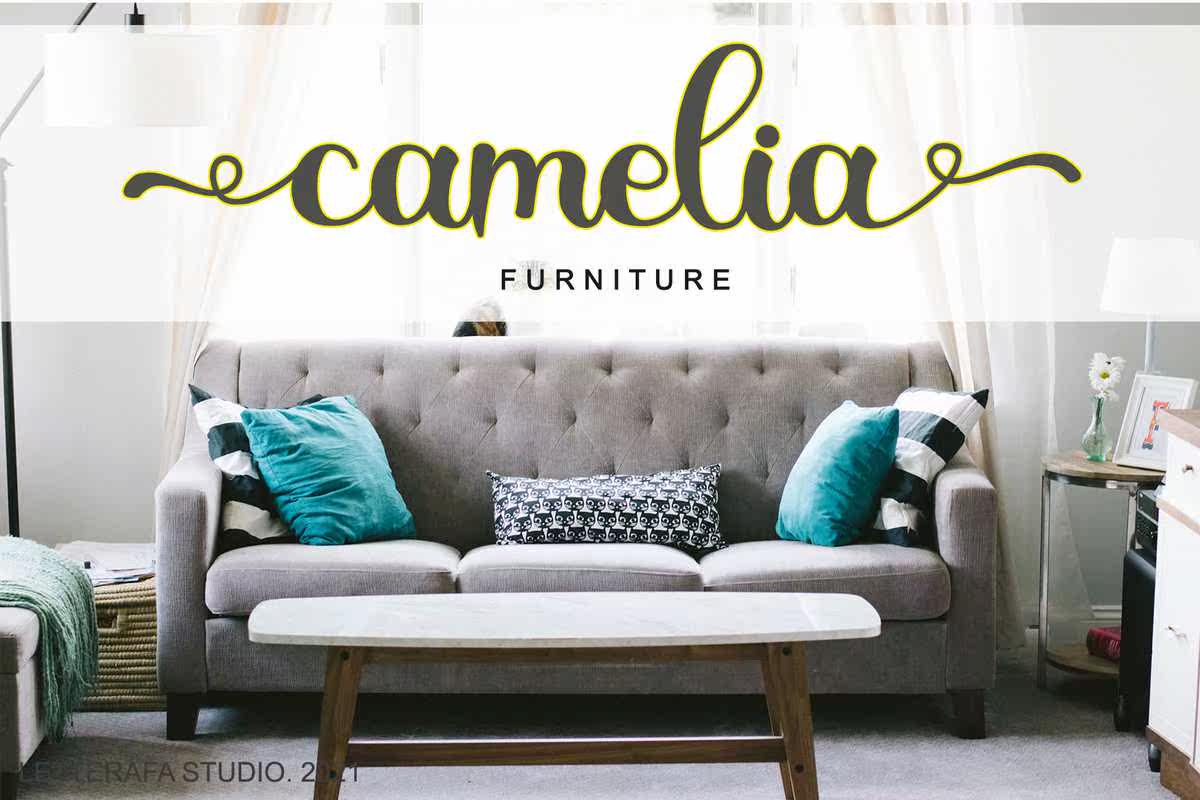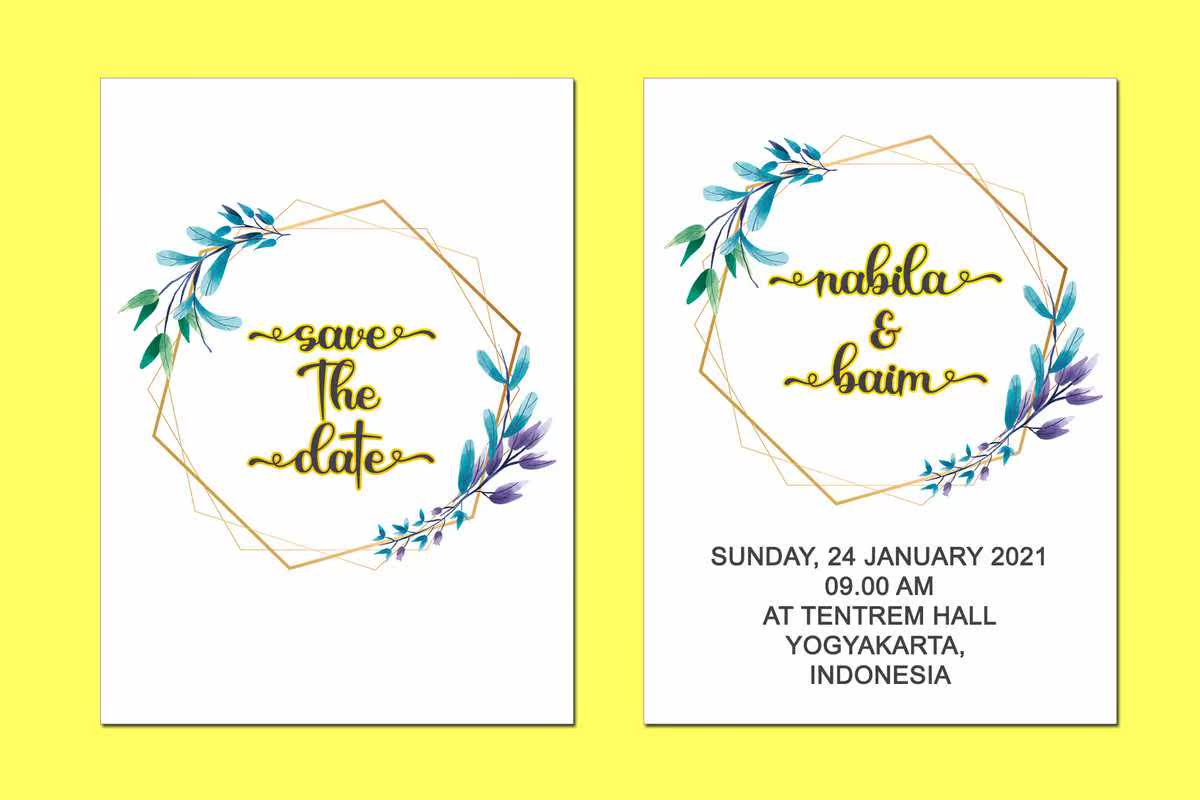
EastersToryFont是一个现代化的AlligraphyFontBylettRafaStudio。它具有流动的字母,可以让您的设计和周视图具有许多灵活的字符。EasterStoryfontisperfect;徽标、问候卡、包装设计、耐磨性、工艺设计、任何项目、书名、婚礼宣传、包装等。Easters ToryFont是一款现代化的AlligraphyFontByletterRafaStudio。它的流动字母将为您的设计和周间提供许多生动的特征。Easters ToryFontIsPerfect;徽标、问候卡、包装设计、耐磨性、工艺设计、任何项目、书名、婚礼宣传、包装等。